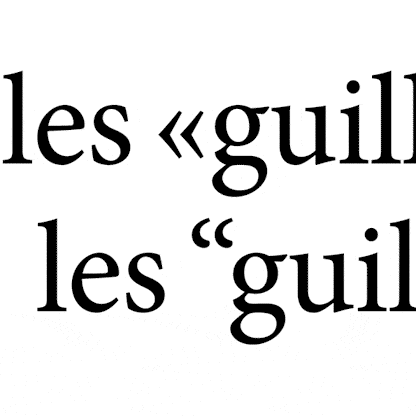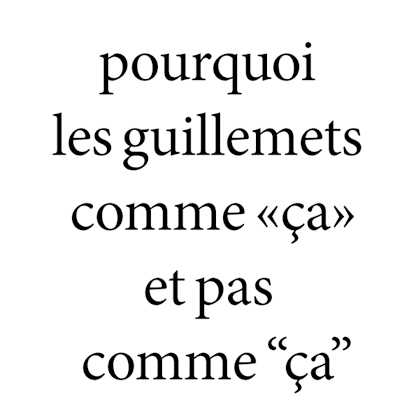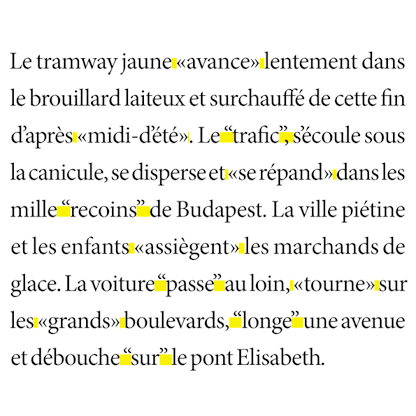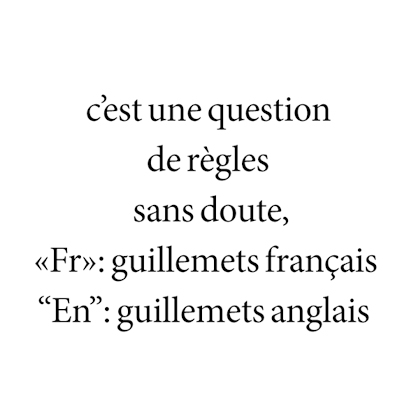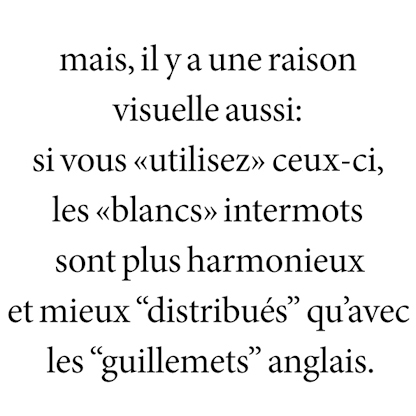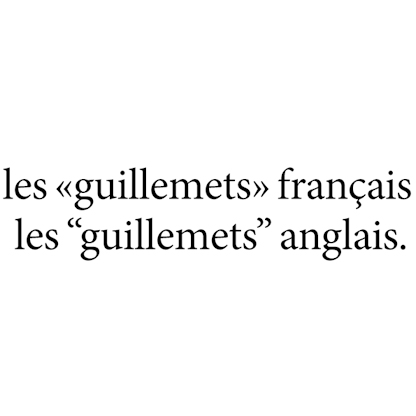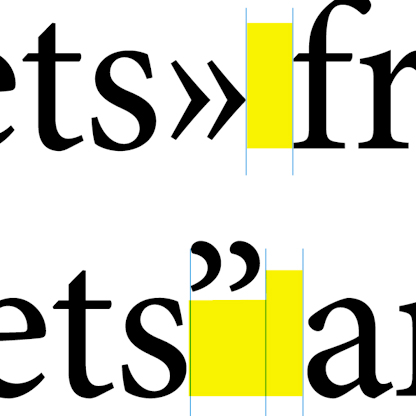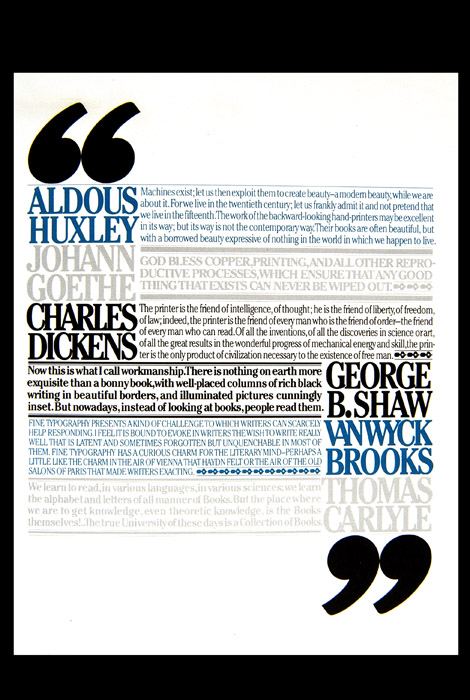
Guillemets anglais ou guillemets français | Un choix graphique (reloaded)
Il y a longtemps que je voulais faire un billet sur cette question des ponctuations. Nous travaillons tous de plus en plus des textes bilingues et bien entendu le typographe devient schizophrène car, et c’est légitime, les équipes de SR, correcteurs, et autres chefs de projets chez les clients ont tout de même appris (merci Word) que les règles de ponctuation changeaient selon la langue utilisée.
Alors oui il y a aussi une troisième voie, concernant les guillemets, celle qui a été choisie par exemple par la rédaction du Monde, d’utiliser ni la règle anglaise, ni la française… de banals guillemets droits tous droits sortis d’un film d’horreur à la gloire du tout « informatique ». J’avais déjà signalé les aberrations que cela pouvait susciter: [je vous l’avais bien dit: l' »Angleterre de Wilkinson n’a laissé aucune chance au XV de France ».]l' »on voit bien que les guillemets se confondent avec les apostrophes » en créant une illusion de ponctuation… sans aucune précision. Il eût été bien entendu bien plus heureux d’écrire l’«Angleterre de Wilkinson…». Ensuite bien entendu il y a tous les débats sur les espaces que l’on doit rajouter entre les guillemets et le texte qu’ils ouvrent et qu’ils ferment. Une fine insécable disent les uns, un espace normal, les autres… l’espace normal (s’il n’est pas insécable) se retrouve malheureusement bien souvent à la fin d’une ligne, rejetant la ponctu à la ligne suivante. Malheureux.
Personnellement j’utilise, l’espace très fine d’InDesign qui me satisfait de son insignifiance. Ou pas d’espace du tout.
Alors quid des guillemets «chevrons» à la française… Bien que connotant vieille France, édition, beau livre etc. ils permettent de construire «un gris typographique» bien plus régulier que les guillemets à l’anglaise. Et l’on voit bien dans les différentes figures ci-dessous le pourquoi.
J’ai surligné en jaune les espaces que libèrent chaque type de guillemet. Les chevrons s’architecturent dans le texte sans créer de rupture dans la ligne de lecture.
Les crochets au contraire créent des accidents qui dans les textes courant ne sont pas très heureux. Je dis les textes courants, parce que ce n’est évidemment valable que pour ces derniers. Dès qu’il s’agit d’un titre, d’un mot composé en grand, et servant d’accroche à une publicité, une couverture de livre, et autres emphases de mise en page, les crochets anglais reprennent leur intérêt tant leur assymétrie et leur sensualité servent la mise en scène graphique.
Où l’on voit les espaces courir sous les guillemets anglais en créant des trous d’air dans la lecture.
Ici une composition qui mélange les deux types de guillemet.
La même composition où nous mettons en évidence les espaces provoqués par les deux types de guillemet. Bien entendu il n’est pas besoin d’en rajouter, les guillemets français s’articulent plus intelligemment dans le texte.
Nous avons vécu durant des années sur les préceptes d’un code typographique promu et défendue par feu l’Imprimerie Nationale. Déjà Pierre Simon Fournier avait en son temps tenté de «normer» la composition typographique, mais en ces temps reculés la France était le centre du monde. Avec le village global ce n’est plus le cas. Internet redécouvre la typographie et malgré ses lacunes (composition justifiée avec algorithme de césure fine), nous assistons à l’apparition d’un mélange entre plusieurs traditions, anglo-saxonnes et francophones. Le Print tente encore de résister, avec les SR et responsables de projets qui nous rappellent sans cesse les codes en vigueur. Jamais cependant la question de l’esthétique n’est abordé. Au point que l’on nous bassine encore avec de vieilles règles d’espace devant et derrière les guillemets français, alors que cela fait cinquante ans que les graphistes tentent d’imposer la suppression de l’espace entre le guillemet et le mot qui le suit. Nombre d’entre nous avons préféré la demi-mesure d’un espace «fine» ou «ultra-fine»…
Il m’apparaît en tous les cas salutaire de rappeler la règle la plus importante pour mettre tout le monde d’accord. Quelque soit vos choix de ponctuations, appliquez-les du début à la fin d’une édition, voire d’une collection. L’important étant l’homogénéité intrinsèque. Vers une mondialisation du Code Typographique… sans doute. Mais de grâce n’abandonnez pas le double chevron des guillemets français… C’est tellement plus élégant dans une belle édition ou dans la presse. À quelques exceptions près :